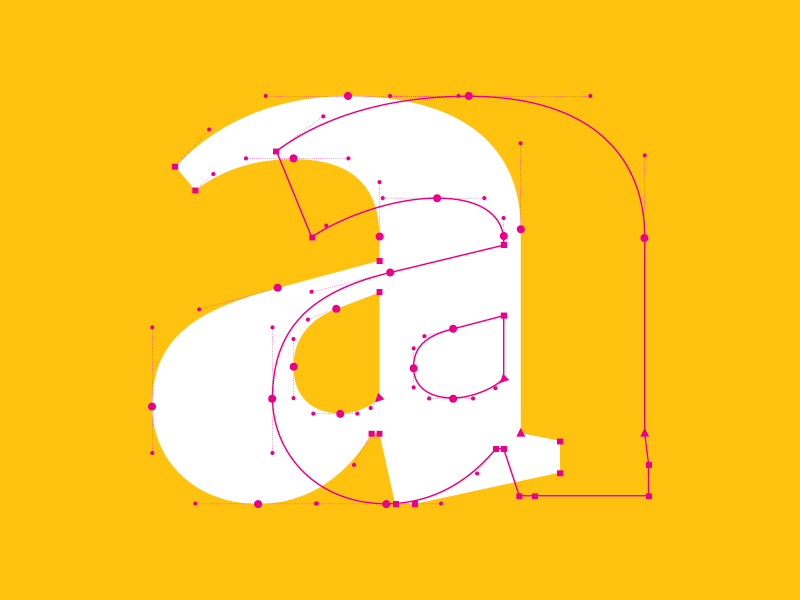
[デザイン革新]フォントの新時代!バリアブルフォントがグラフィカルUIに与える影響
2019年に流行すると見込まれるユーザーエクスペリエンスのデザインの中から、バリアブルフォントをいくつか列挙しました。バリアブルフォントの今後の展望を予測する時がきています。いまだにバリアブルフォントが予想されていたほど普及していないのは、ユーザーインターフェースに組み込む普遍的な方法が確立されていないからです。
デザイナーらはすでに、バリアブルフォント機能がフィグマに実装されるよう要求していて、私たちはそれがいずれ実現すると信じています。そうは言っても、バリアブルフォントの重要性やそれが使途に応じたデザインにもたらす影響を理解することは重要です。バリアブルフォントの存在意義や使い方、おしゃれなフォントの具体案、そしてバリアブルフォントを実際にインターフェースに組み込む方法を詳しくみていきましょう。
形状とグリフギャップ
レスポンシブデザインは、その汎用性の高さが代名詞です。しかし、ウェブデザインとコピーライティングのコア資産のひとつであるフォントは、完全で静的な表現に制約されています。デザインに一般的に使用されるほとんどのタイプフェイスは、時代遅れのデザイン原理の名残です。
初期のウェブサイトは、文字や写真を挿入する際にテーブル(表)を使用していました。従来の印刷媒体の構成を模倣しているので、そのやり方には合点がいきました。よりデザインが複雑化するうちに、デザイナーらはシンプルなブロックをいくつも重ね、文字とFlashエレメントを交互に配置しました。CSSの新たな登場で、デザイナーらはより自由自在なデザイン編集が可能になり、やがてそれがフラットレスポンシブデザインに繋がりました。
ウェブデザインが進化し続けていくと、タイポグラフィも独自の発展を遂げていきました。工学よりも美学を追求していた時代だったのです。デザイナーらは、固定されたタイプフェイスを用いてテキストブロックを埋めつつ、流れるようなデザインを作成することができるようになりました。
形状は変化し、使用用途に適していく一方で、グリフは規定限界値の範囲内にとどまります。
ある時期になるとタイプフェイスは陳腐化し、デザイナーらはカスタムタイポグラフィを使用し始めましたが、カスタムフォントの制約を打ち破ることができず、それはまもなくして柔軟性を失いました。
一時しのぎの策
フォントフェイスが3つでは十分ではないと、レスポンシブデザインへの対応策をフォント作成者に強く要求しました。書体デザイナーは、それにフォントファミリーで対応しました。フォントファミリーとは、適宜にサイズ変更が可能なフォントのバリエーションのことです。そのファミリーが大きければ大きいほど、フォントの柔軟性は増し、より汎用可能な領域が広がります。最大のフォントファミリーはシャープ・グロテスクで、259個のフェイスがあります。確かにそのフォントは汎用性を兼ね備えていますが、このようなファミリーを何百個も保管することを想像してみてください。悪夢でしかありません。
フォントファミリーにはある一定の柔軟性を与えていますが、タイプライブラリがビヒモスのように巨大化してしまうでしょう。
フォントファミリーがデザイン通りに表示されるには、アクセス機器にもフォントが存在している必要があります。フォントの有無をコントロールするまでは手が及びません。各種事前インストールが課題です。2019年までにユーザーエクスペリエンスがさほど円滑でなく、バックグランドプロセスの不備を隠し切れない場合、そのウェブサイトは機能しなくなります。
バリアブルフォントの使用理由
レスポンシブフォントを作成する目的で、静的フォントが初めて使用されはじめたのは2014年頃です。ニック・シャーマンとクリス・ルイスはFTW(Font to Width)プロジェクトを立ち上げ、マルチ幅とマルチウェイトをもつフォントファミリーがレスポンシブデザインの枠内にぴったりとフィットするように調整しています。これが、バリアブルフォントの強い後押しとなりました。
ガーディアンは独自開発された巨大フォントファミリー、その名も「ガーディアン」を使用しています。現在は、「日刊新聞のすべての活版印刷のニーズ(重大なニュースの見出し、特集記事、読みやすい文章、細かな財務表、インフォグラフィック、そしてその他諸々)に応える7つのフォントファミリー」で構成されています。640種類にのぼるフォントは、卓越したグラフィック・デザイナー2名が5年もの歳月をかけて手がけたものです。
もし、タイプフェイスに精通していない場合、フォントの違いに気がつく可能性はほとんどないでしょう。潜在的なレベルでいうと、フォントの違いがコンテンツのヒエラルキーと動態の理解を可能にしています。さらに日常的なレベルだと、文章構成にかかる時間を最適化するのは合理的です。
バリアブルフォントはスーパーファミリーをガーディアン・サンズとガーディアン・エジプシャンの2つに限定しています。
バリアブルフォントをガーディアンの出版過程に取り入れることで、いくつものタイプフェイスファミリー間の密なコネクションが維持されつつ、異なるコンテンツに適当なフェイスを決定するプロセスが著しく簡素化されます。その一方、デザイナーらは一般的なデザインに応用可能なタイプセッティングの通義を学ばなければいけなくなるでしょう。
バリアブルフォントの柔軟性のみに頼るわけにはいきません。実のところ、バリアブルフォントを使用する際には、フォントの選択肢以上に全体的に洗練されたデザインが求められます。
バリアブルフォントは柔軟で、細字と太字の両極端の間であればどの大きさにも変更が可能です。複数のステップを介さず多次元空間内で変化します。バリアブルフォントはアニメーションのようなキーフレームと呼応しています。限界値は設定されておらず、タイプフェイスもまた同様です。同フォントは高度な処理能力を必要とせず、僅かなサーバーリクエストでより速やかにロードし、タイプフェイスがベースのデザインの自由度を高めています。
時間が限られている時には、バリアブルフォントは非常に有効です。従来のフォントとは異なり、バリアブルフォントに必要なのは一通りの座標軸とグリフごとの動作指示のみです。複数のカスタム軸を左右に移動し、レスポンシブウェブのレイアウトのようにテキストを変形します。しかし、これには各タイプフェイスの視認性の原則との兼ね合いを考慮にいれないといけません。詳しくみていきましょう。
バリアブルフォントは、多次元で無限に広がるあらゆるデザイン空間を駆使しています。
バリアブルフォントの線形補間によって、アニメーションを作成する新たな代替方法が打ちだされています。ローディング時間やフレームサイズ、接続問題により、デザイナーはアニメーションを控えることを余儀なくされています。バリアブルフォントの性能があれば、4KBのディスク容量に加えて数百バイトのHTMLを持つフォントでこのようなアニメーションの制作が可能です。
これは、アクシス・プラクシスが打ち出したバリアブルフォントの方向性のうちのひとつの機会に過ぎません。
読みやすさ
異なる印刷条件がタイプフェイスの読みやすさを左右します。仮に、ライティングコンテンツが総じて文章の読みやすさに主眼を置いているならば、グリフのサイズや正確性を高めながら、それを維持し続けるための最善を尽くしていかなければいけません。しかし、スペースを広げるだけでは不十分です。新聞はフォーマットを均一に揃えなくてはいけません。文章の直接編集、ページの追加または画像数の縮減で対応が可能です。
デジタルメディアの場合、新聞よりさらに複雑です。手動修正はレスポンシブデザインには対応していません。画面の解像度に応じて内容を編集することは不可能なのです。多くの場合、モバイル端末向けのレイアウトだと、すべてのスペースが文章で埋め尽くされ、画像が表示されなくなってしまいます。
こちらがヴァージというサイトのデスクトップとモバイル解像度です。
ある企業はネイティブアプリを搭載し、ウェブコンテンツを複製することで問題に対処していますが、それに加えてデバイスの解像度にも合わせて修正しています。
読みやすくするには、画面サイズを問わず文字は常に同じサイズでなければいけません。
視覚補正
複数のデバイス解像度でも同水準のエクスペリエンスをもたらすには、タイプフェイスを変更し、読みやすさを格段に上げる機能でデバイス環境を補わなくてはいけません。従来は、タイポグラファーはオプティカル・サイズの概念を用いて、同じ活字の大きさのあらゆるフェイスで視認性が認められていました。デジタルの場合、バリアブルフォントにオプティカル・サイズ軸が追加されたことにより、サイズに特化する条件のもとで視覚補正がもたらされています。
例えば、ベントン・モダンには3つのオプティカル・サイズ、48種類のスタイル、そして4つの幅に対応したディスプレイ・スタイルがあります。オプティカル・サイズは数学的に計算され、画面解像度とテキストボックスのサイズに応じて適用されます。
画面が縮小するのに合わせて、フォント変更で視認性を高めながらも、本来のデザイン選択時と同様のフォントの見た目を維持しています。
タイプフェイスに視覚補正機能が搭載されている場合、デザイナーは適切なフォントの選択とその固定位置を把握しておく必要はありません。たいていの場合、試行錯誤が重ねられています。仮にバリアブルフォントに補正機能が付随しているならば、フォントは自動調整されます。
エックスハイトが8ピクセルでも、判読可能です。
視覚補正とは、人間の視覚に基づいた数学的パラメーターです。
デザイナーらは、試行錯誤を重ねてこの効果を追求しています。それは、バリアブルフォントの原理に間違いなく起因すると考えられています。
バリアブルフォントコントロールとユーザーインターフェース
バリアブルフォントの操作方法を理解するには、フォント利用者を把握する必要があります。仕事の一環や日常生活の中でタイプする人々は、バリアブルフォントの潜在的なユーザーだと、私たちは考えています。バリアブルフォントはただのデザインツールではないのです。なぜなら、私たちは文章を介して遥かに多くの問題を解決しているからです。伝達が第一だとすれば、デザインは二の次です。ただ間違いなく、バリアブルフォントが大衆の手に届くのは、デザインツールのおかげです。
意味のある文章と相まって、バリアブルフォントが世界情勢の解釈を一変する可能性を秘めています。しかし、より多くの人がバリアブルフォントを利用できるようになると、誤った使い方が横行する恐れもあるでしょう。
バリアブルフォントは、デザイナーの責任にゆだねられています。
操作の実行の仕方によって、バリアブルフォントは期待に応えるか、一時的な流行で立ち消えするか、いずれかに落ち着くでしょう。バリアブルフォントの行く末は、自動操作の量とユーザーに与えられている選択肢に直接関連しています。選択肢を提供すればするほど、プロセスの影響力は弱まるでしょう。手動操作とバックグランド設定のバランスを探ることが、バリアブルフォントによってコントロールされたインターフェースが発展可能かどうかの鍵を握っています。
わたしたちは、利用可能なバリアブルフォントインターフェースを二重構造だととらえています。第一層はシンプルな2本または3本の軸のコントロールと設定の多くがはっきりと目に見えています。そのようなユーザーインターフェースは、利用可能な設定数に圧倒されることなく、柔軟に使用方法を提供できます。
第二層はプロの領域です。ここには、フォントに影響を与えるようなエミュレート済みの物理的環境条件などを含むあらゆる変数を組み込むことが可能です。ただ、常識や美学に基づいた不変パラメーターを一定程度維持することは重要です。
結局のところ、バリアブルフォントツールの真価はそれがもたらす満足感ではなく、デザイナーの創造力に頼ることなく、サポートと安全がもたらされることです。
今のところ、バリアブルフォント専用の実践運用可能でかつ普遍的なユーザーインターフェースの原則は存在しません。しかし、いずれそれがデザインの主流となり、そこからグーグルやマイクロソフトの製品の開発に進んでいくでしょう。バリアブルフォントの発展はまだまだ続きます。